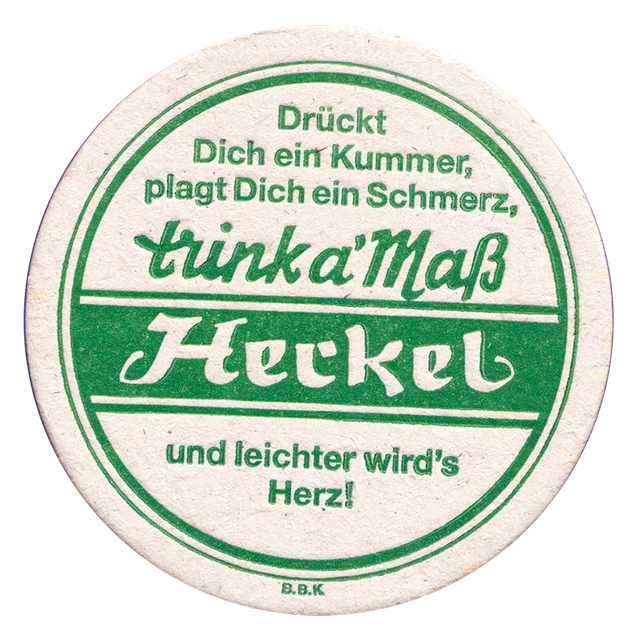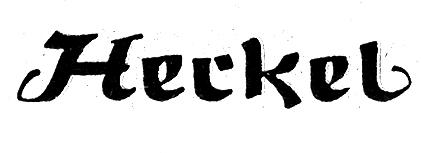
Gebrochene Schrift von Brauerei Heckel gesucht
ich versuche die Schrift im angehängten Bild zu identifieren.
Bei myfonts, fontshop und fontinuse habe ich keine Schrift gefunden, die in diese Richtung geht.
Muss nicht unbedingt die gleiche Schrift sein. Es wäre für mich schon ein großer Erfolg, den Namen für die Schriftklasse herauszufinden.
Dieses flache ›e‹ finde ich einfach nirgendwo.
Hier ein paar Eckinformationen:
1. Der Schriftzug stammt von einer Bierdeckel. Gründungsjahr ca. 1900.
2. Der Schriftzug stammt aus Bayern.
3. Es gibt keine weiteren Buchstaben, die in dieser Schrift gesetzt sind.
Dass die beiden unterschiedlichen e alleine schon drauf hinweisen, dass der Schriftzug gezeichnet ist, sollte klar sein. Von der Idee her, wie die Striche zusammengesetzt sind geht es Richtung Rotunda oder Rundgotisch – für Bier nicht ganz unüblich.
Aber irgendwie auch maturalike: